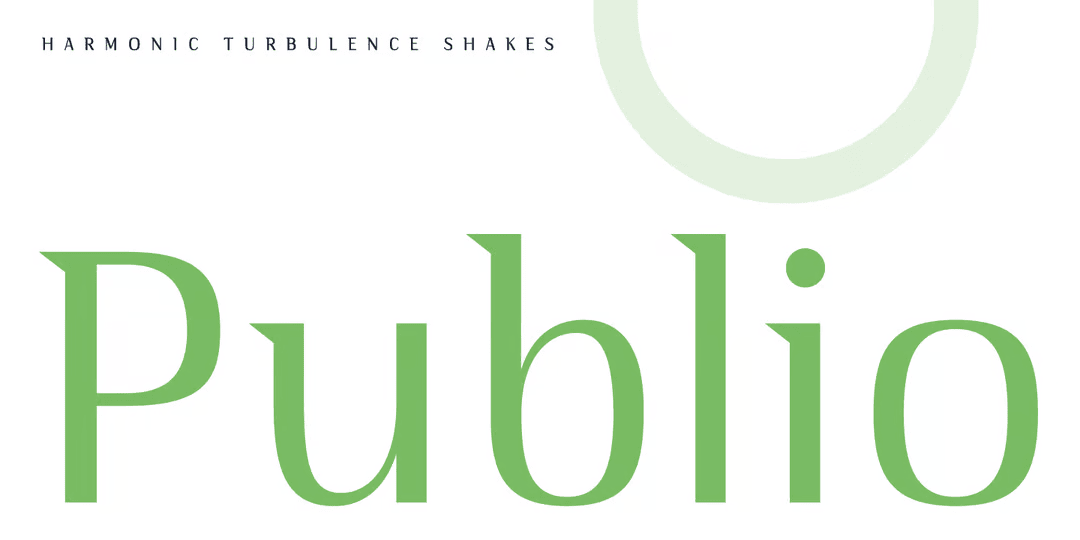
Publio
すっきりクリーンなセミセリフディスプレイ。シンプルでゆったりしたグリフに一部ちょこんとセリフの付いた読みやすい書体で、ストロークはややコントラストあってエレガント。大文字は素直なグリフだが小文字はちょっと変わっており、p などステムとボウルがある字はステムが一部欠いてあったり、g のループが小さくオープンになっていたりしていて個性的。シャンプーやボディソープなど、女性向けのトイレタリー製品のロゴにありそうである(笑)。イタリックと2スタイル。